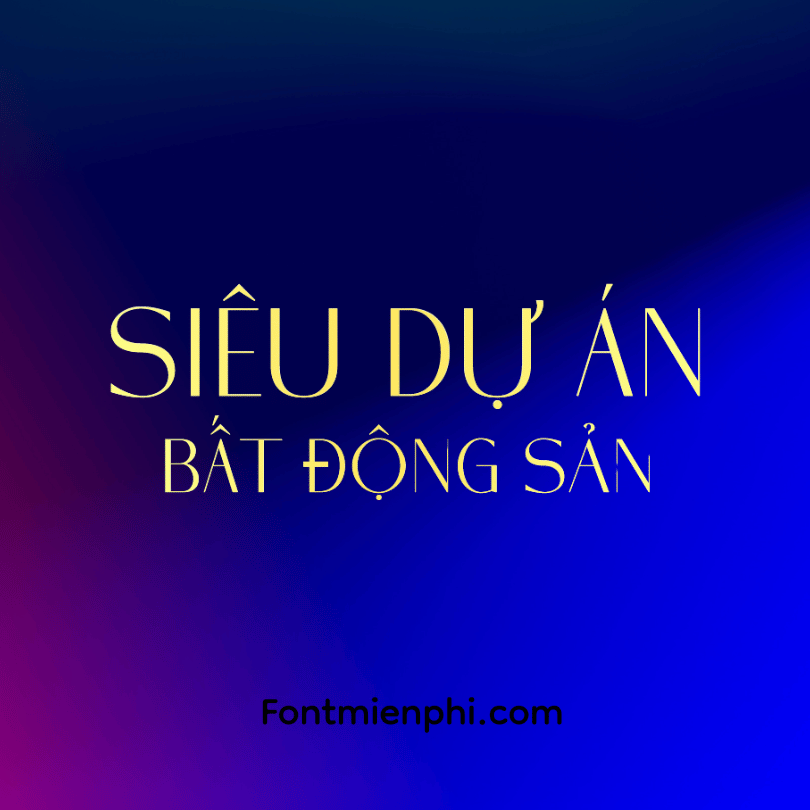
Font Việt Hóa 1FTV VIP Opaline – Thanh Lịch Tinh Tế Từng Nét Chữ
Đặc điểm đắt giá:
• Phong cách minimalist luxury với nét chữ mỏng nhẹ như sương
• Việt hóa hoàn hảo, tối ưu cho mọi văn bản Tiếng Việt
• 4 biến thể cao cấp: Light, Regular, Bold và Italic
• Độ phân giải cực khủng, in ấn rõ nét ở mọi kích thước
✓ Phiên bản VIP có kerning được tối ưu hoàn hảo